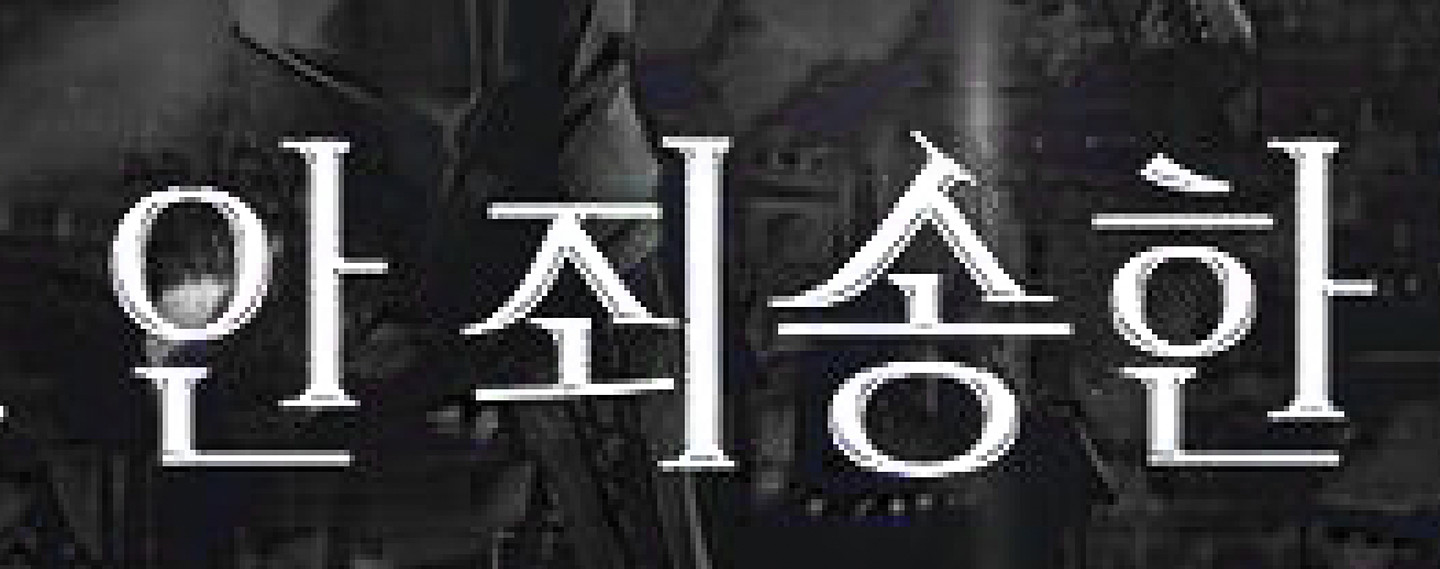
이거 무슨 폰트일까요...? 웹소설 표지에서 본 폰트인데 아무리 찾아도 없네요..ㅠㅠ 직접 그리신 건 아닌 것 같은데
기존 폰트에서 변형하여 직접 그린겁니다만, 기존 폰트는 잘 모르겠네요. 개인적인 생각으로는 시티산스에서 변형한 것 같습니다. ㅎ 이나 ㅚ 의 획 모양이 같아서요.